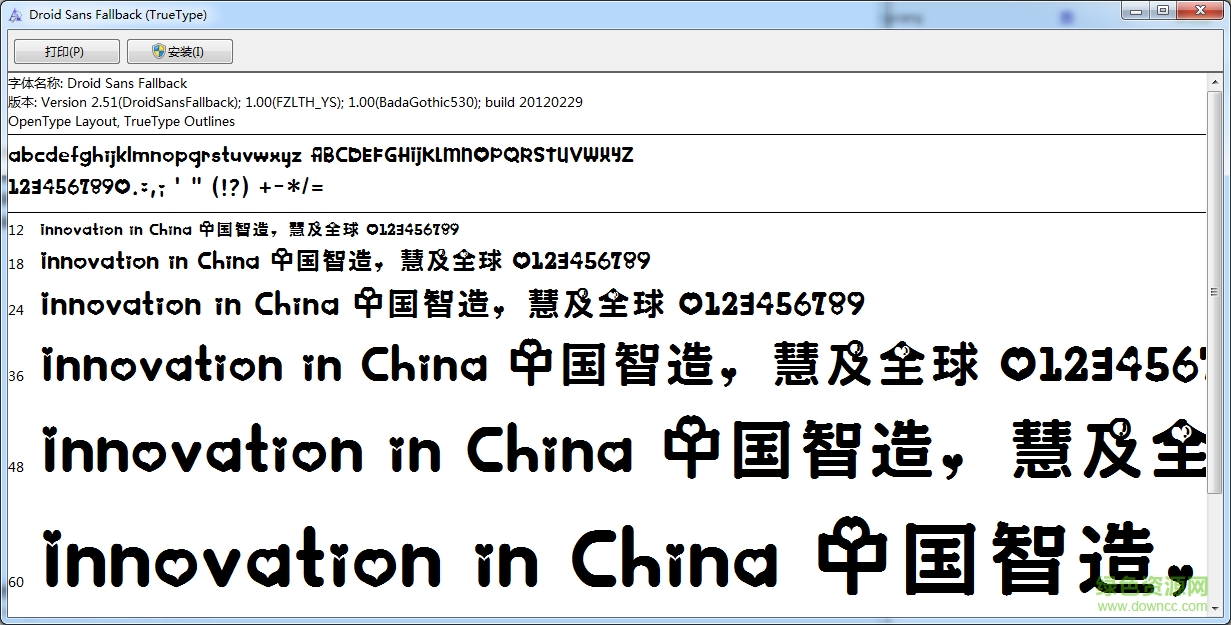
愛(ài)情當(dāng)心有所屬字體是一款藝術(shù)設(shè)計(jì)字體。字體圓圓的,比較卡哇伊。字體上面帶有精致的心形狀。常被用來(lái)做美術(shù)設(shè)計(jì)使用!喜歡的朋友快來(lái)綠色資源網(wǎng)下載吧。
愛(ài)情當(dāng)心有所屬字體是一款用于胖體設(shè)計(jì)方面的字體!獨(dú)特的心形字體讓你的周圍充滿了愛(ài)的氣息,是婚禮和求婚活動(dòng)現(xiàn)場(chǎng)文字用的字體,絕對(duì)讓你加分再加分!